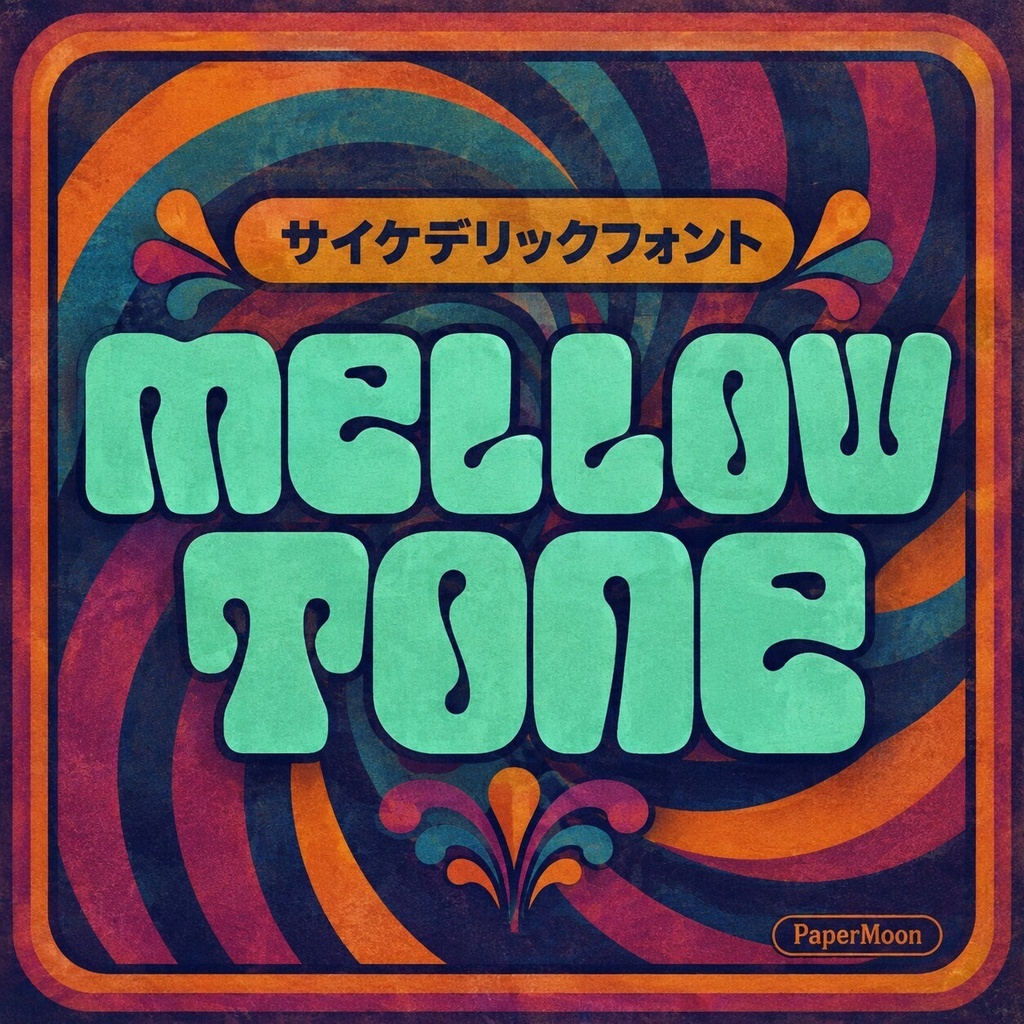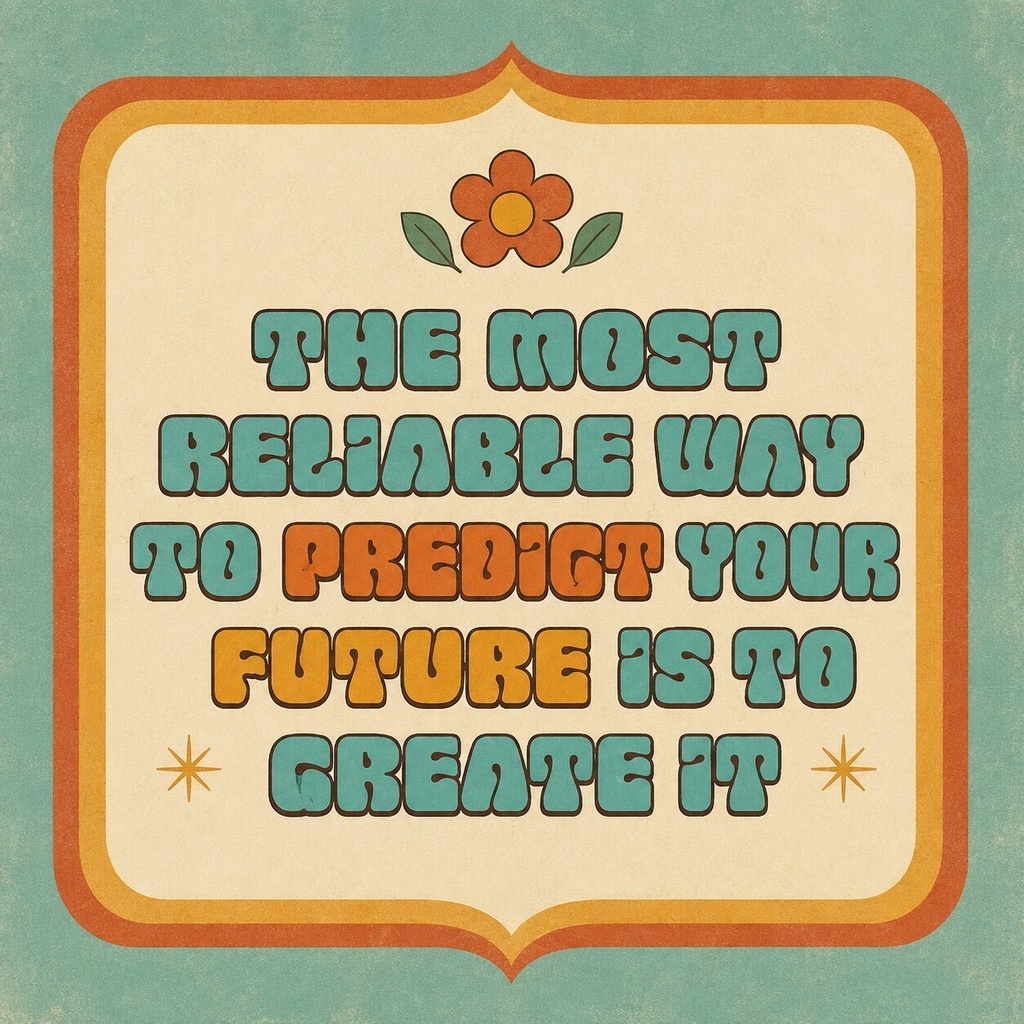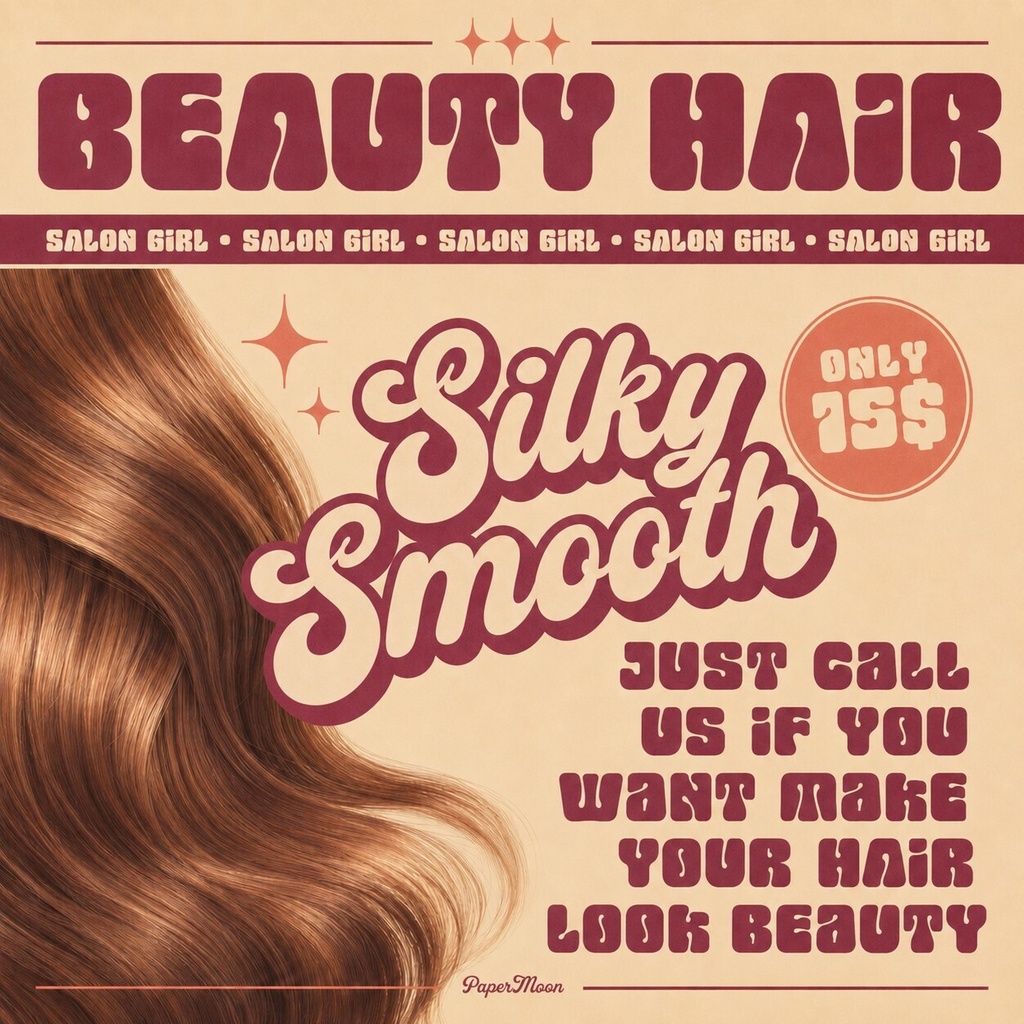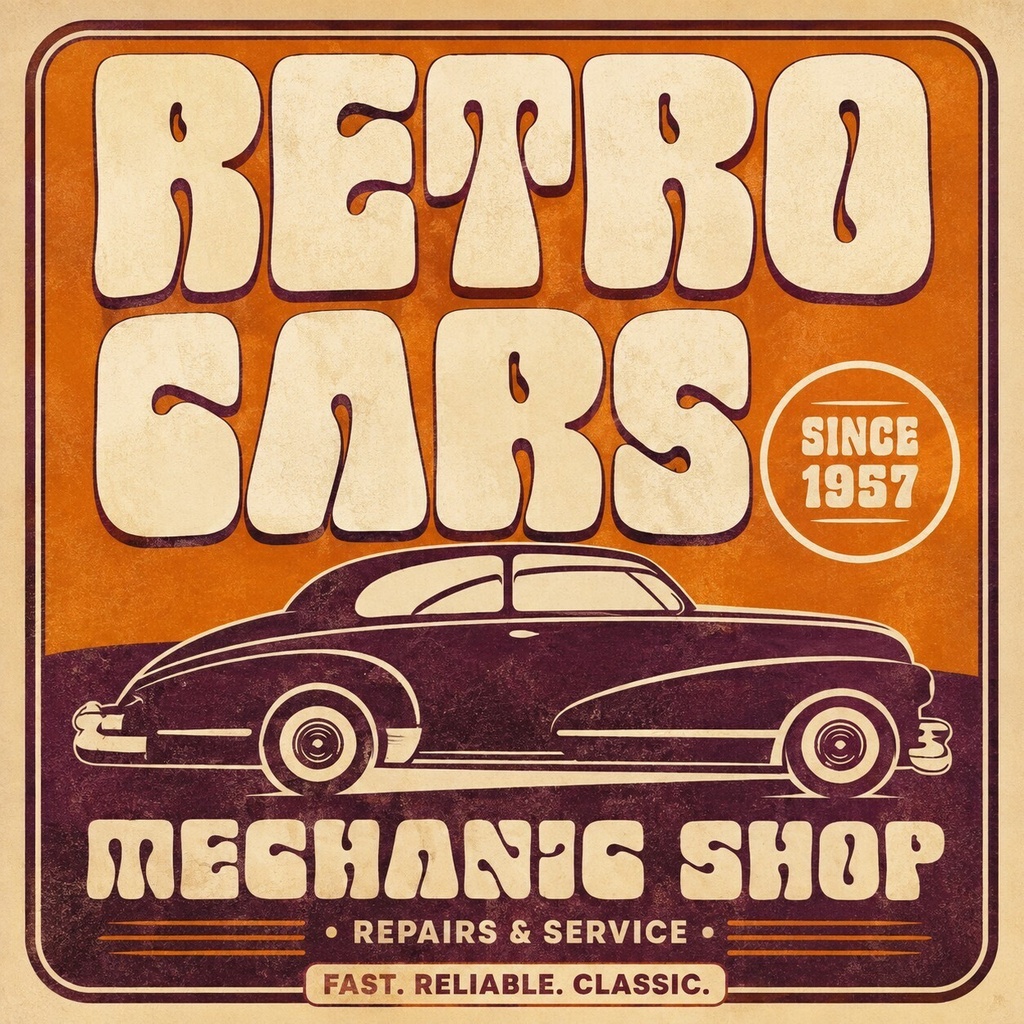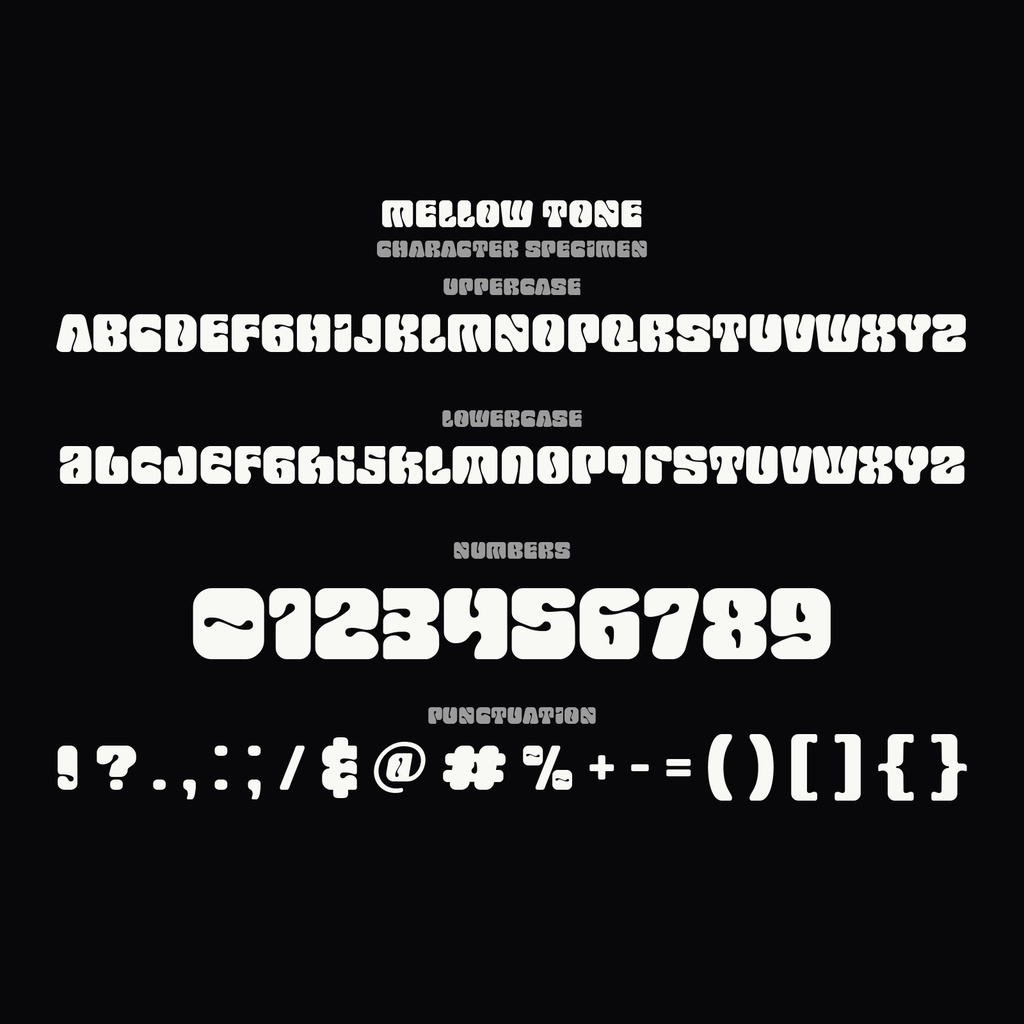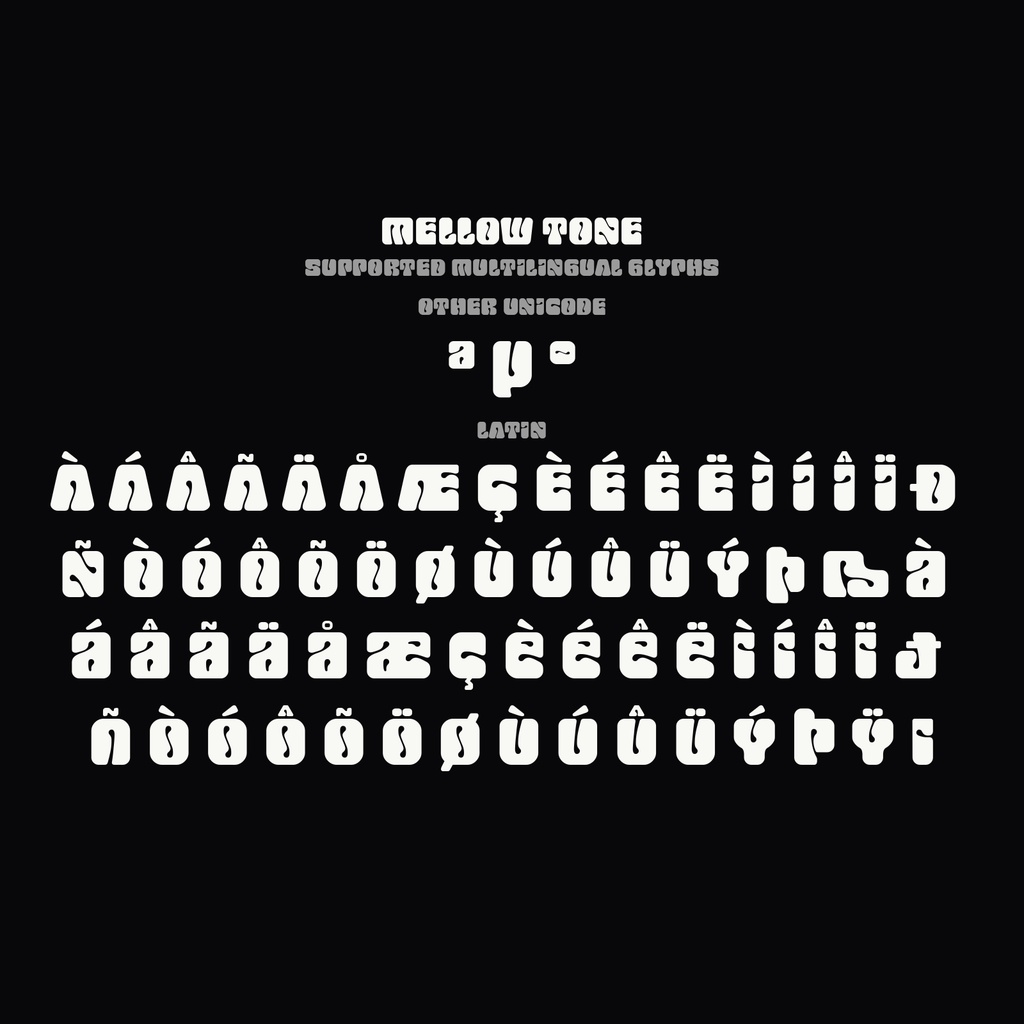
Mellow Tone | レトロ・サイケデリックな丸みのある欧文フォント | ロゴ・ステッカー・パッケージ向け
Mellow Toneは、丸みのあるタッチでレトロなサイケデリック感を表現する欧文フォントです。やわらかく印象に残る文字の雰囲気で、短い言葉やタイトルに個性と楽しさを加えます。 ロゴ、ステッカー、パッケージデザイン、見出し、ブランドづくり、ポスター、雑誌、書籍、動画やSNSのグラフィックなど、目を引く文字表現におすすめです。Cricutを使った制作や、YouTube、Instagram、Webなどのクリエイティブにもご利用いただけます。 ### 収録内容 - Mellow Tone Regular - 大文字・小文字 - 数字・句読点 - 多言語対応 ### 対応文字 大文字・小文字、数字、句読点を収録し、多言語に対応したフォントです。 ### 用途 ロゴ、ブランド名、ステッカー、パッケージ、ポスター、雑誌、書籍、見出し、Cricutプロジェクト、YouTube、Instagram、Webなど。 ### 形式 デスクトップ用:OTF / TTF ウェブ用:WOFF / WOFF2 ### 対応環境 OTFまたはTTFをインストールできるフォント対応環境でご利用ください。WOFFおよびWOFF2は、対応するWeb制作環境で使用できます。Cricutなど、外部フォントを読み込める対応ソフトやサービスでの利用を想定しています。 ### 利用許諾 商用利用版と個人利用版の2種類があります。事業、クライアント制作、有料制作、ブランド、収益化、広告、商品・グッズなどには商用利用版をお選びください。購入者本人の非商用作品、学習、練習、個人的な制作には個人利用版をご利用ください。具体的な利用範囲、再配布、埋め込み、再販などの条件は、購入するバリアントのライセンス本文をご確認ください。 Mellow Toneで、レトロで遊び心のある文字表現をお楽しみください。